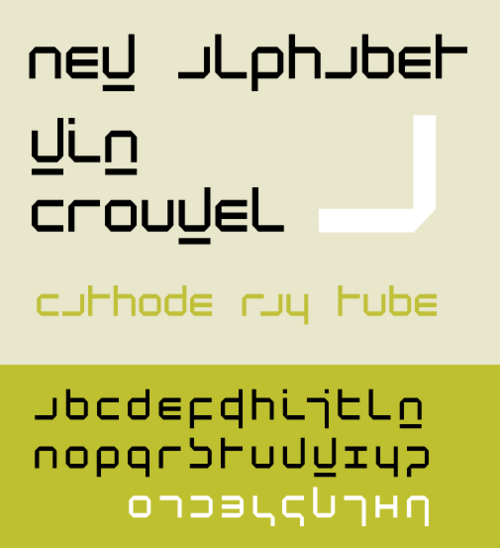
| カテゴリ | サンセリフ |
| デザイナー | ウィム・クロウエル |
| 鋳造所 | ザ・ファウンドリー、ロンドン |
New Alphabet は、 Wim Crouwelがデザインし、1967 年にリリースされたパラメトリック書体です。水平線と垂直線のみを使用することで、表示に使用されたディスプレイ技術の制限に対応しました。そのため、一部の文字は、本来表現する文字とほとんど似ていません。New Alphabet は、Joy Divisionの 1988 年のコンピレーション アルバムSubstanceのカバーで特に使用されました。
歴史
ニューアルファベットは、クロウエルの個人的な実験的なプロジェクトでした。この書体は、初期のデータ表示画面や写真植字機で使用されていたブラウン管技術の制限を取り入れて設計されたため、水平線と垂直線のみが含まれています。従来の書体は、詳細レベルが十分でないため、可読性が制限されるため、これらの制限に悩まされる可能性があります。クロウエルは、デザインに合うように技術を適応させるのではなく、デザインを新しい技術に合わせて適応させたいと考えました。[1]彼の文字の形には水平線と垂直線のみが含まれているため、一部のグリフは従来どおりではなく、他のグリフは、それらが表す文字のどのバージョンともほとんど類似していません(いくつかの例では、頻繁に表示される aグリフはJに、K はtに、数字の1 は7に、数字の8 は大文字のHに、xグリフは大文字のIに似ています)。このため、この書体は同僚から複雑な感情で受け止められました。
ほとんどの文字は、45度の角を持つ5×7単位のグリッドに基づいています。各グリフは、必要に応じてアセンダ、ディセンダ、またはティトルを追加した、正方形の2つ以上の辺で表されます。3本の水平バー( E、3)を持つグリフは忠実に表現されますが、3本の垂直バー(M、W)を持つグリフは忠実に表現されず、それぞれ下線付きのNグリフとVグリフで表さ れます。大文字と小文字のグリフを区別するために、大文字には小文字の上部に追加の水平線が追加されます。
クロウエルの同僚の多くは、このデザインは実験的すぎ、やりすぎだという意見だった。この書体は新聞で大きく取り上げられ、芸術としての書体と日常的な使用における実用性を比較する活発な議論が巻き起こった。[2]クロウエルは批判にほぼ同意し、これは主に理論上の演習であると指摘し、2009年に「ニューアルファベットはやりすぎで、実際に使用されることを想定していませんでした。読めませんでした。」と述べた。[3]
New Alphabet は、 2011 年 1 月にニューヨーク近代美術館が建築とデザインのコレクションのために取得した 23 のデジタル書体のうちの 1 つです。この書体コレクションは、MoMA が最初に取得した書体の一部であり、2011 年から 2012 年にかけて開催された「Standard Deviations: Types and Families in Contemporary Design ( Standard Deviations)」という展覧会で展示されました。
使用法
ジョイ・ディヴィジョンの1988年のコンピレーションアルバム『サブスタンス』のアルバムカバーにはニューアルファベットが使われており、アルバムタイトルは「subst1mce」に相当する文字で綴られている。カバーを手がけたブレット・ウィッケンズは、これは美的理由によるものだと主張した。1991年のアルバム再発盤には、同じスタイルではあるものの異なるアートワークが使われており、「substance」という単語は綴られておらず、アートワークにはニューアルファベットの書体で大きな緑の「S」が描かれている。
デジタルニューアルファベット
New Alphabet は、1996 年にロンドンの The Foundry の Freda Sack と David Quay によってデジタル化されました。これはArchitype 3 Crouwel Collectionの一部であり、3 つのウェイトで構成されています。元のコンセプトは 3 つのウェイトに限定されず、パラメトリック システムとして意図されており、マシンのパラメーターを変更することでさまざまな形状を作成できるようになりました。
2015年、ジョシュア・クーメンはオリジナルの指示書に基づいて、ウェブアプリの形でニューアルファベットの デジタル[4]版を開発しました。このアプリケーションにより、ユーザーはニューアルファベットのあらゆる設定を作成できます。